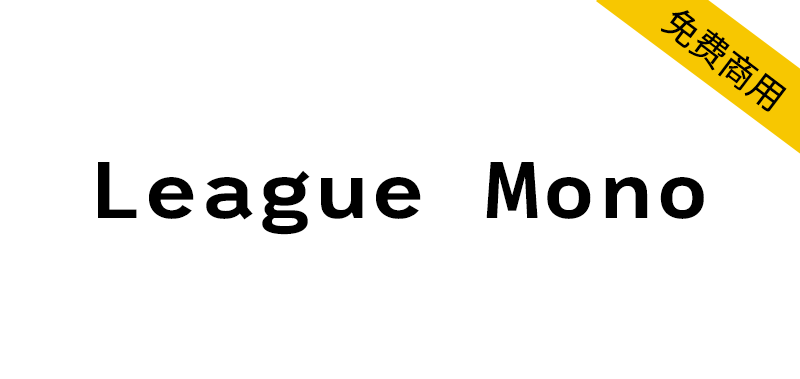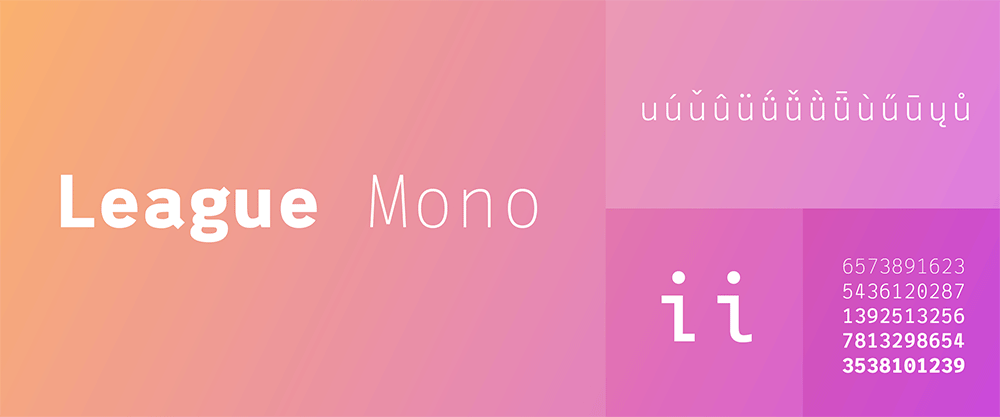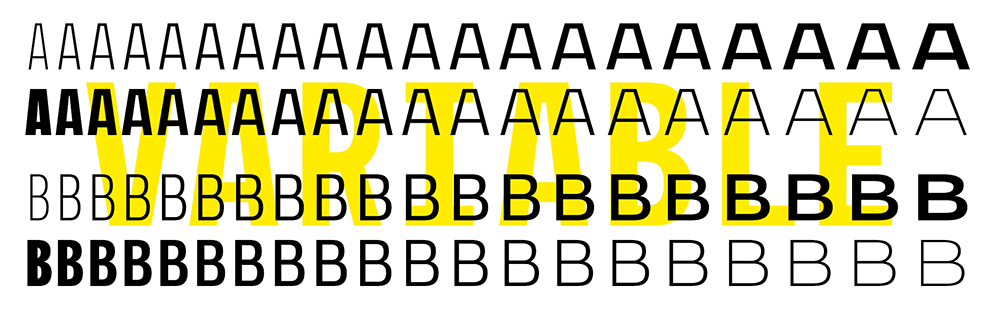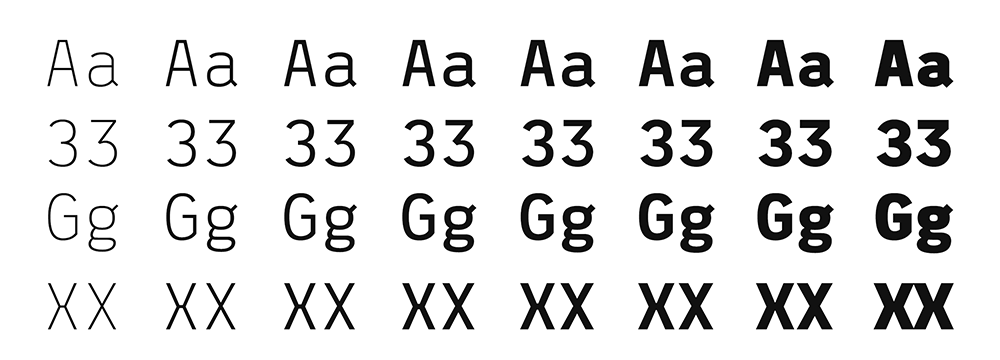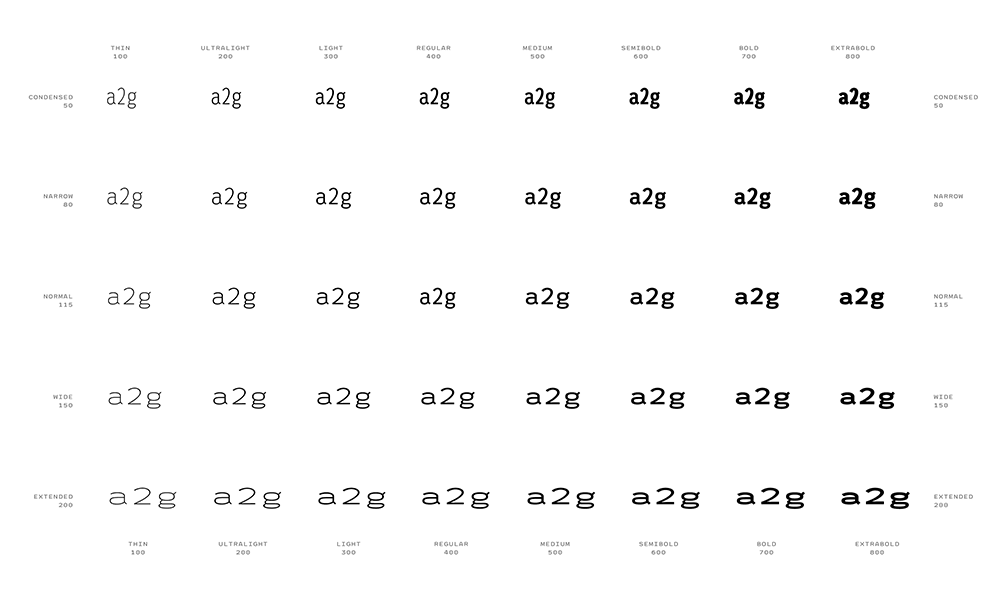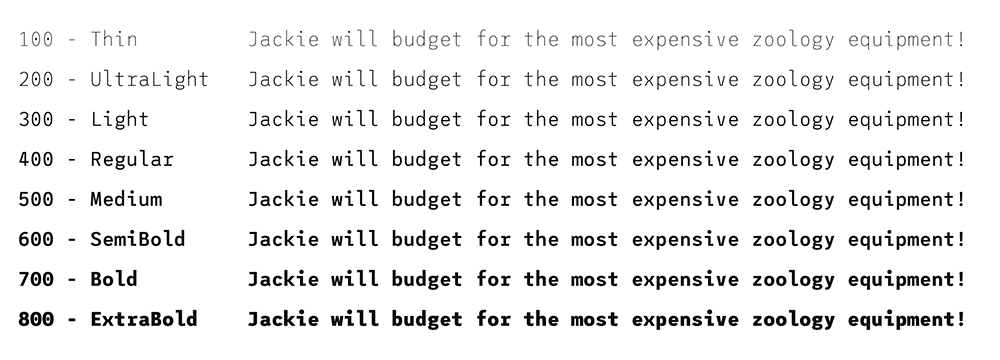
League Mono 是一款混合风格的等宽字体,其灵感源自 Fira Mono、Libertinus Mono 和 Courier 等宽字体中一些优美的字形设计。(League Mono is a mashup of sorts, inspired by some beautiful forms found in both Fira Mono, Libertinus Mono, and Courier(?!).)